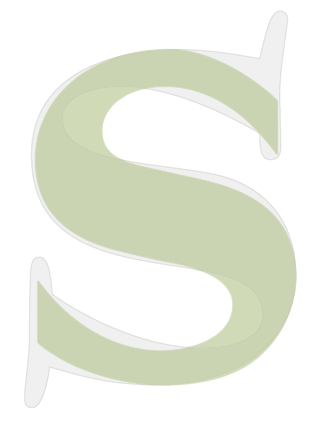
Aus welcher Typo ist das Berliner S-Bahn "S"?
Ist im FF Transit-Package (FF Transit Produkt, liegt auf dem s) enthalten.
Ich kann mich finster entsinnen (also: meine Erinnerung verschwindet fast im Dunklen, meine Stimmung ist hingegen heiter und gelöst. Ihr wißt schon, wie ichs meine.), dass wir eine uralte Reproduktionsvorlage hatten, Sorte Normungsblatt/Urzeichnung von der ausgehend wir, die Form dabei natürlich sanft modernisierend, das S-Bahn-Signet für das Transit-Paket umgesetzt haben. Ich würde sagen, diese Urzeichnung war nicht im heutigen Sinne "entworfen" ... Moment mal, es klingelt.
Ich würde sagen, diese Urzeichnung war nicht im heutigen Sinne "entworfen"
was war sie dann? wie alt ist denn das zeichen eigentlich?
die schlechte, freie, umsetzung bei wikipedia im svg-format ist aber
nicht von dir oder? brrr... http://de.wikipedia.org/wiki/Bild:S-Bahn-Logo.svg
Dann löse ich mal meine neblige Aussage auf:
Nicht entworfen = geometrisch konstruiert
Ich erinnere mich an Zirkelpunkte auf dem Zeichnungsblatt.
Und oben und unten waren bei der Zeichnung vertauscht, haha.
Diesen alten Faden buddele ich mal aus, denn inzwischen gibt’s viele neue Erkenntnisse zum S-Bahnzeichen.
Nüchtern liest sich die Meldung vom 24. Dezember 1930 im amtlichen Nachrichtenblatt der Deutschen Reichsbahn-Gesellschaft (DRG) Die Reichsbahn: Berliner S-Bahn. Die Berliner Stadt-, Ring- und Vorortbahnen werden künftig kurz „S-Bahn“ heißen.
Dem voraus ging eine recht krampfige Namenfindung zwischen Frühsommer 1929 bis 10. März 1930. Die Große Elektrisierung der Berliner Stadt-, Ring- und Vorortbahnen war im wesentlichen abgeschlossen. Nun suchte man bei der Reichsbahndirektion Berlin (Rbd Bln) nach einer griffigen Kurzbezeichnung als Werbung bzw. Bahnhofshinweis. Jedoch hatte die Hauptverwaltung der Deutschen Reichsbahn-Gesellschaft (Hv der DRG) diesen Bestrebungen einen mächtigen Stein in den Weg gelegt: Weder ein Buchstabe (ein U – wie bei U-Bahn seit 1926 nachweisbar ist) noch ein bildliches Zeichen (z. B. Flügelrad) sollte verwendet werden.
Die Rbd-Leute machten dennoch weiter und experimentierten (listig) mit zwei Buchstaben für Stadt-Schnellbahn (SS-Bahn – politisch war dies noch nicht anrüchig, sperrig war’s allemal).
Die Rbd konnte den hohen Granden der DRG-Hv eine Gedankenbrücke bauen, so daß diese am 10. März 1930 einlenkten: Die Hauptverwaltung hat gegen die Bezeichnung Stadt-Schnellbahn (SS) gewisse Bedenken. Schnellbahn sei im allgemeinen eine Bezeichnung für kommunale Verkehrsmittel. Die Stadt Berlin spreche in einer offiziellen Denkschrift schon im Titel vom Ausbau ihres Schnellbahnnetzes. Die Verbindung Stadt-Schnellbahn deute noch mehr auf ein städtisches Unternehmen hin. „SS“ sei länger und umständlicher als ein „S“, auch in der Darstellung weniger wirksam. ‚Stadtbahn‘ allein sei eine alteingebürgerte Bezeichnung, so dass diese genüge und vorzuziehen sei.
[Endlich! Gebt uns ein S!]
Wenige Tage später ging beim Baudezernat der Rbd Bln ein Angebot (20.2.1930) des Gebrauchsgraphikers Fritz Rosen vom „Atelier Professor Bernhard-Rosen“ ein; Rosen war Partner von Lucian Bernhard, der seit 1925 von New York aus Amerika erobern wollte …
Im Juli 1930 hatte er seinen Entwurf zur Zufriedenheit der Reichsbahn durchgearbeitet, die das Symbol zunächst an einer Bahnbrücke in Charlottenburg erprobte. Rosen bekam 800 Mark für seine Arbeit: je 200 Mark für zwei Entwürfe sowie 400 Mark für die Reinzeichnung und die Überlassung des Reproduktionsrechts. Für umgerechnet knapp 3000 Euro schuf er ein nachhaltiges Werk.
Fritz Rosen – geboren 16.10.1890 in Frankfurt a. M., gestorben 1980 in Brighton (England)
Zunächst war dies ein weißes S und dem Wort BAHN auf einer grünen Grundplatte in der Form eines Bogenfensters. Schon ab 1932/33 verschwand der Wortzusatz – ein Beleg für den großen Erfolg des Begriffs S-Bahn und des S-Bahnzeichens!
Mit dem Bau des Nordsüd-S-Bahntunnels und insbesondere des 1936 eröffneten unterirdischen Bahnhofs Unter den Linden (vor einigen Jahren in Brandenburger Tor umgetauft) bedurfte es einer architektonischen Lösung für die Zugänge im Straßenland: kein Empfangsgebäude – aber jeweils ein Loch mit Treppe in den Untergrund …
Überlagerung des S-Zeichens aus der Originalabbildung von 1930 (hellgrün, nachgezeichnet nach Rbd-Aktenvorlage) mit einem S aus Lucian Bernhards Schriftart Bernhard Modern Bold (grau). Könnte dies die Vorlage für das S-Zeichen sein?